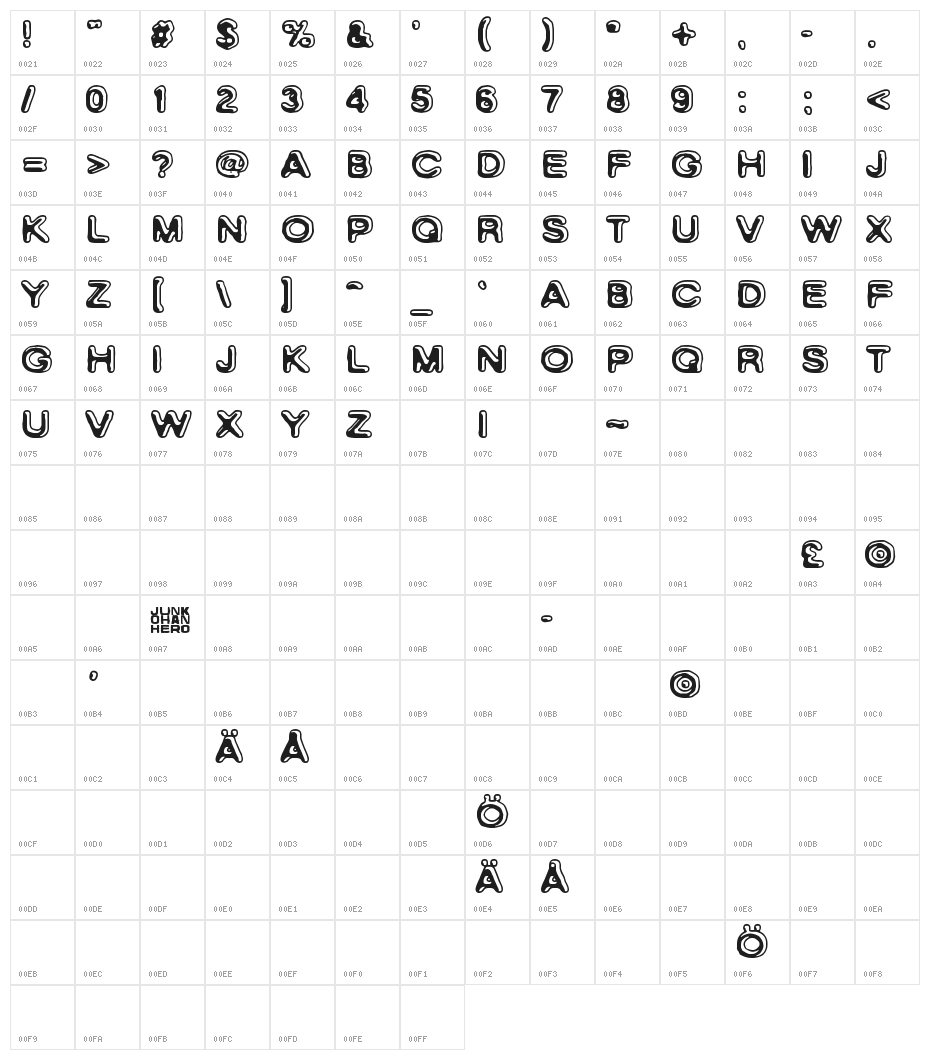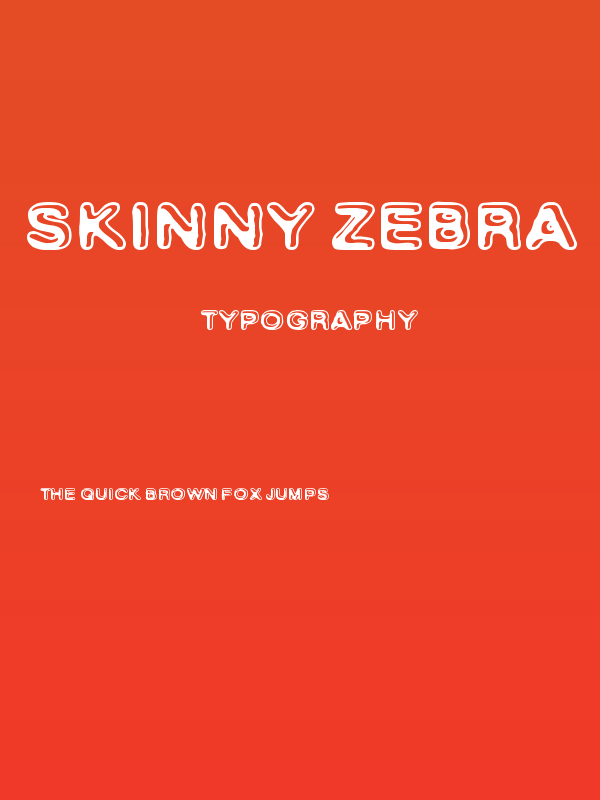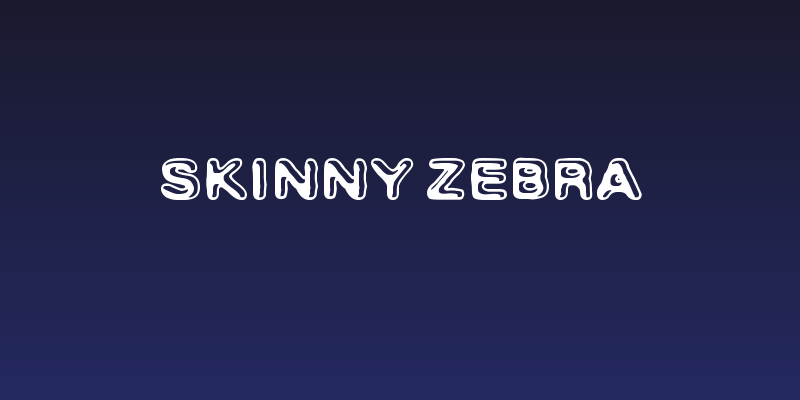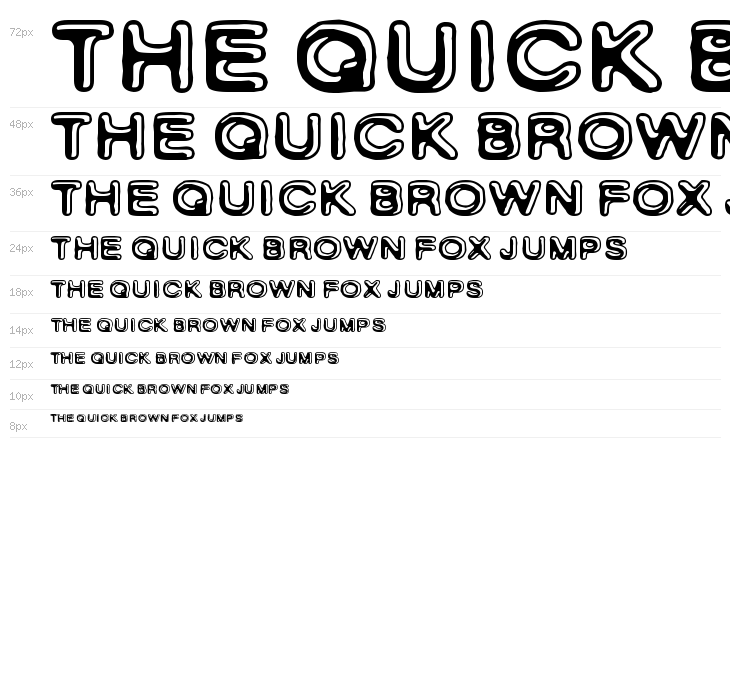
Skinny Zebra Font
| Stil general | Playful, Energetic, Whimsical |
| Proiecte propuse | Perfect for children's books, playful branding, event posters, and creative social media graphics. |